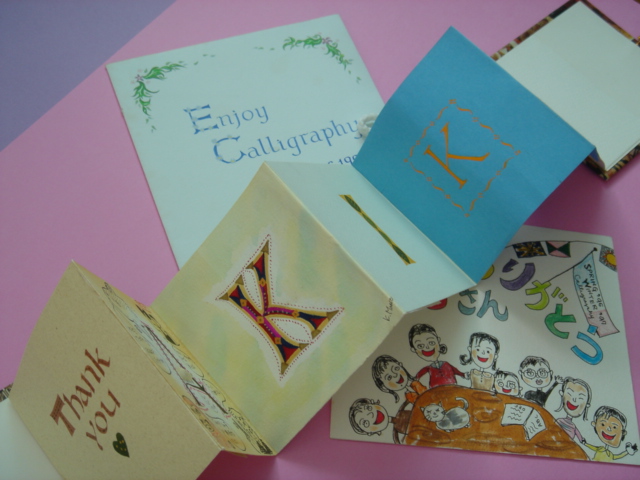
みんなで寄せ書き
そろそろ卒業式の準備も始まっているのでしょうか。
というのも・・・
先日クラスのかたから、卒業時の謝恩会で先生に渡す寄せ書きについて相談されたのです。
だいたい毎年、花束のほかに記念の贈り物をしているそうです。
生徒一人ずつ感謝の言葉を書いて、絵や写真で飾ったりしたものをひとつのアルバムなどにまとめる、というものらしいのですが、今年はそれをアコーディオンブックにまとめたいという考えがあるようです。
その話を聞いて、私の大切箱に入っているカードを思い出しました。
もう何年も前のことですが、しばらく教室を休むことになったときにクラスのみなさんがカードを贈ってくださったのです。真ん中のアコーディオンブックがまさにそれ。
ひとりずつ書いて(描いて)持ち寄ってくれたページを集めています。
私の名前を一人ひとつのアルファベットで書いてくれました。メッセージはそれぞれ裏側に書いてあります。
繊細な文字とボーダー飾りが美しいカードは、中にクラス一人ずの写真をセピア色にして貼ってあり、それぞれに花のイラストとメッセージが添えられていました。当時はスクラップブッキングということばも知りませんでしたが・・・
手前のカラフルなカードは、絵がとってもじょうずな人が似顔絵を描いてくれたもの(ホントに似ています)。内側はいわゆる寄せ書きです。
もう10年近く昔のことですが、このカードを手にとると
そのころのことがすぐによみがえってきます。みんなも私も若かった!
とても大切にしているカードたちです。
別れのシーズン、こんな寄せ書きのカードで気持ちを贈るのもいいですね。